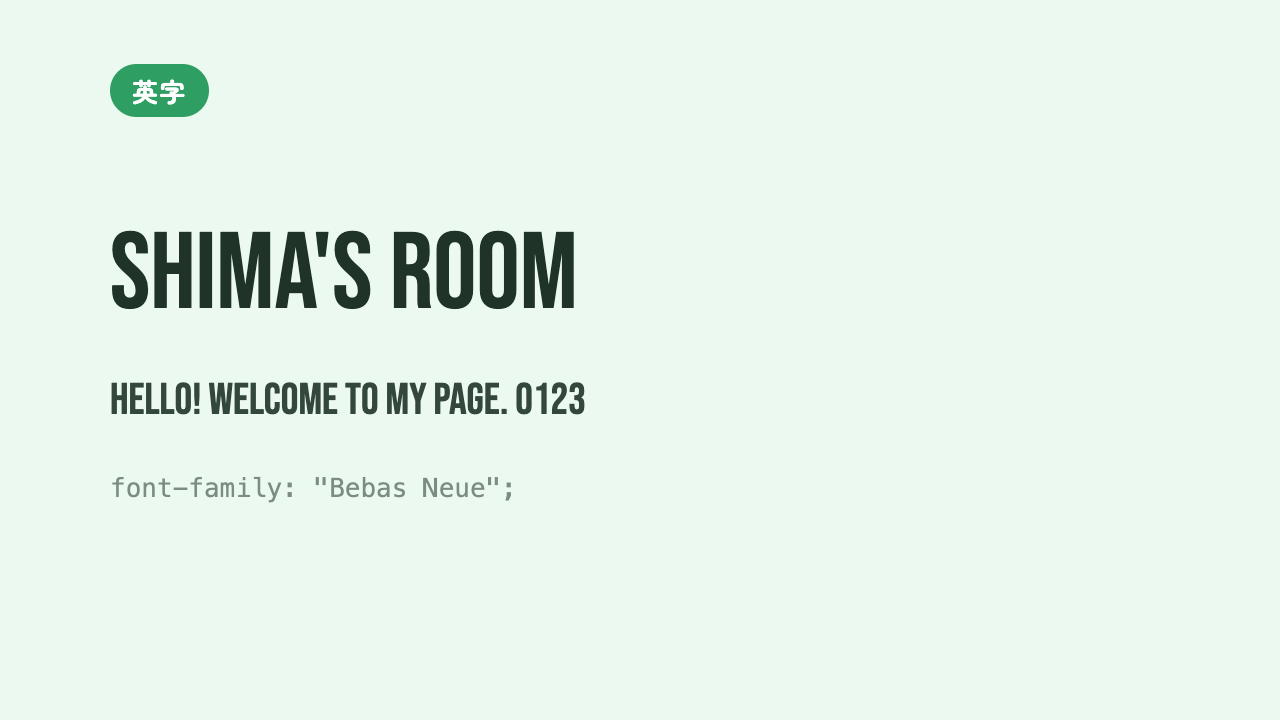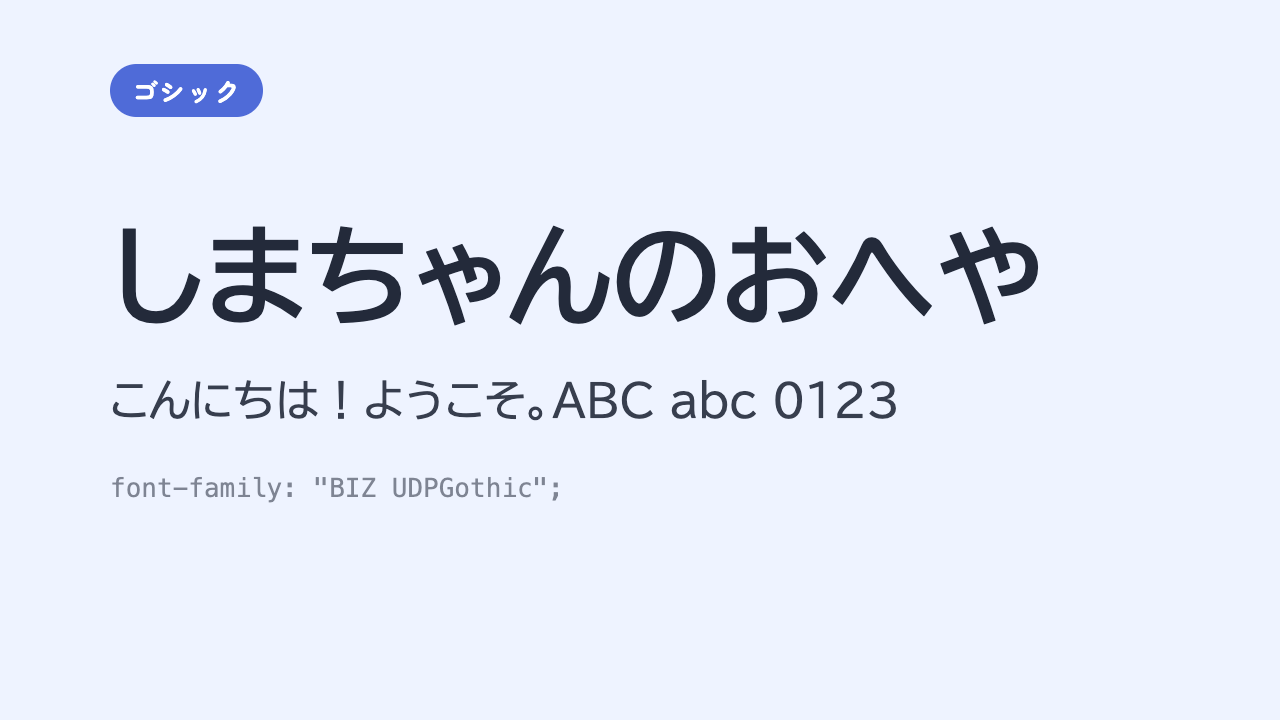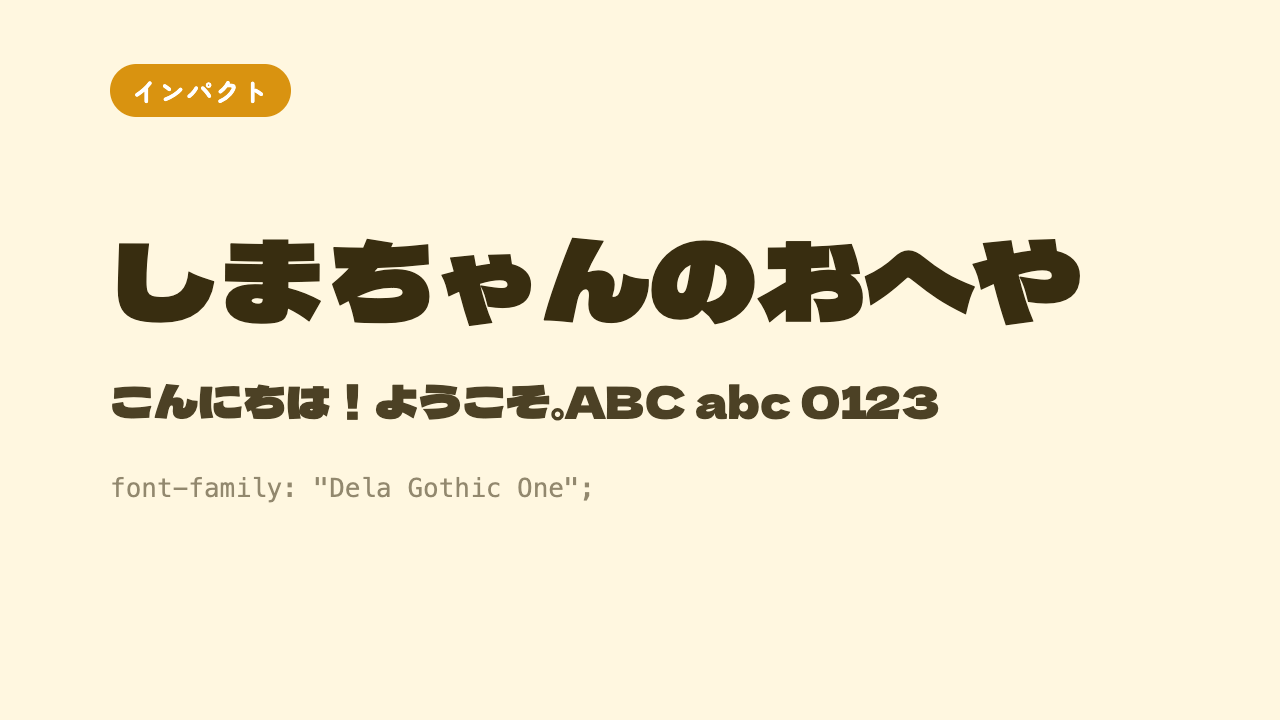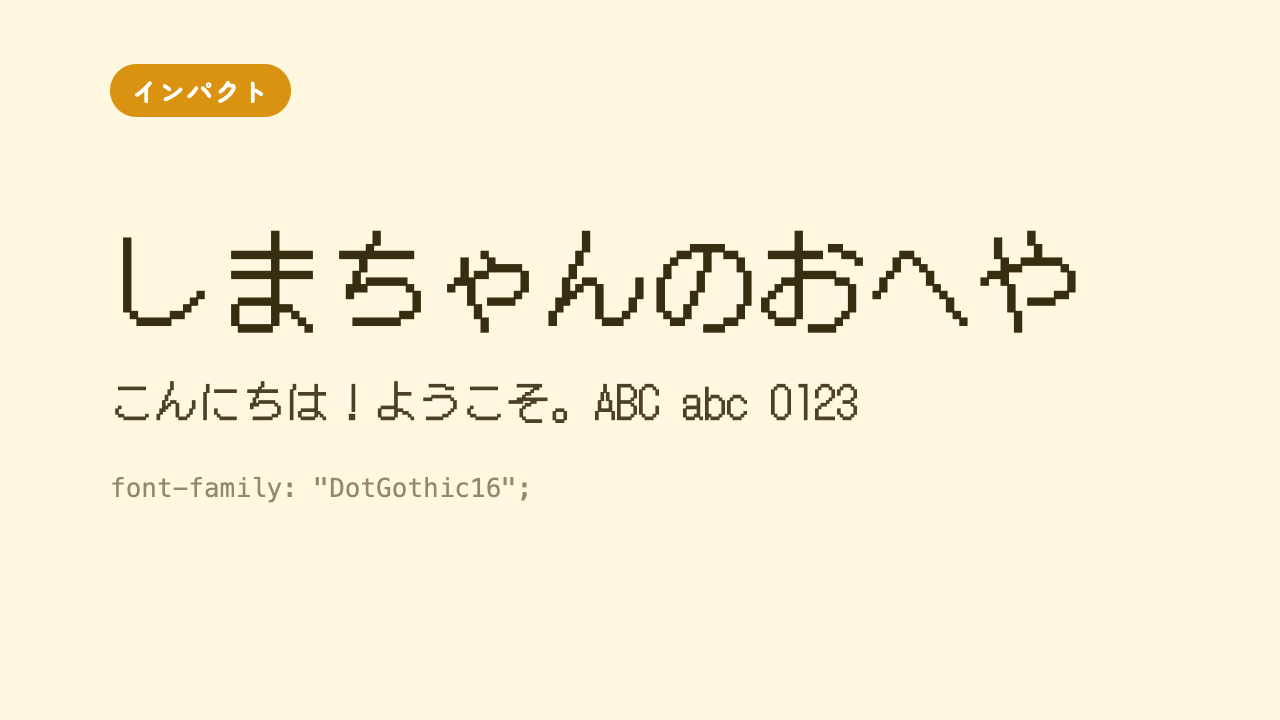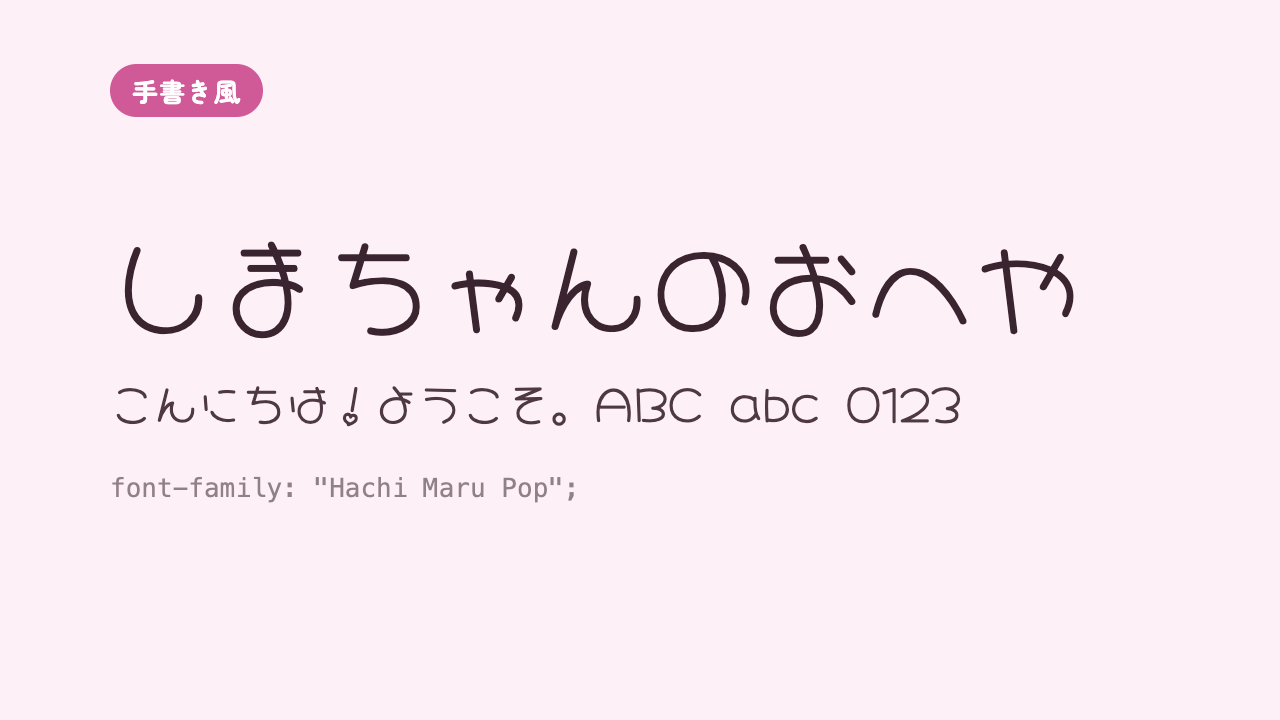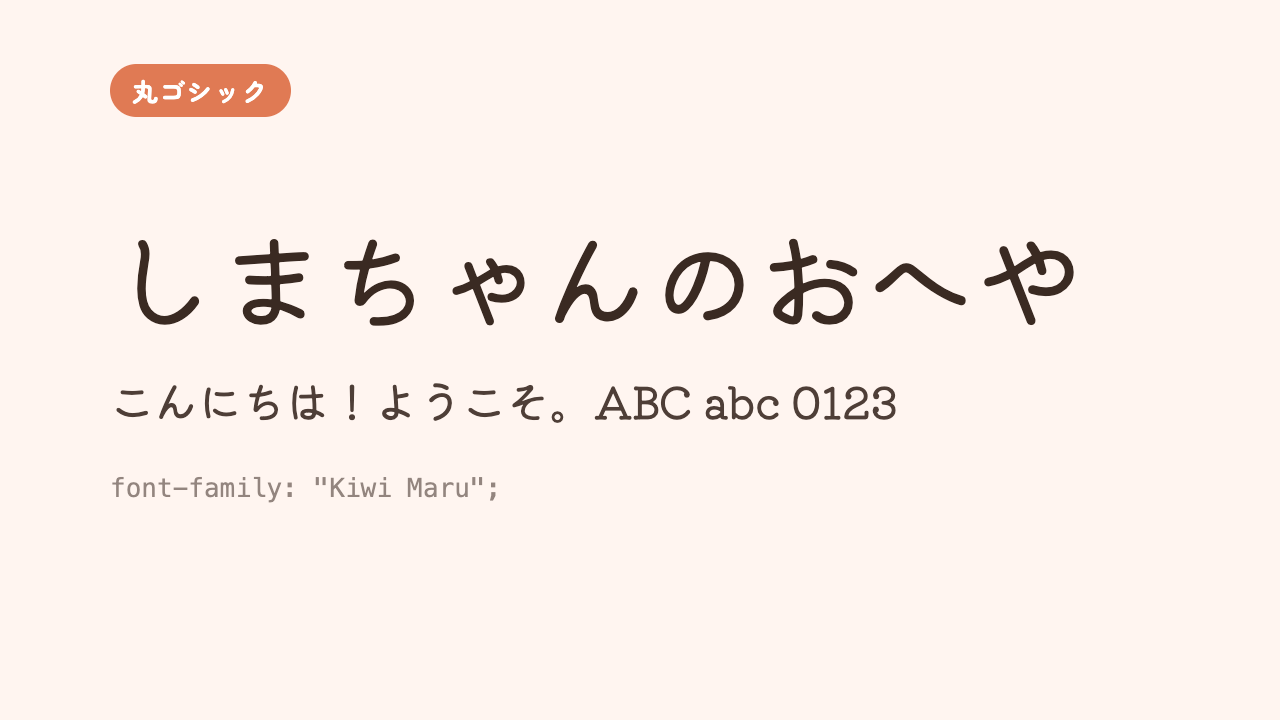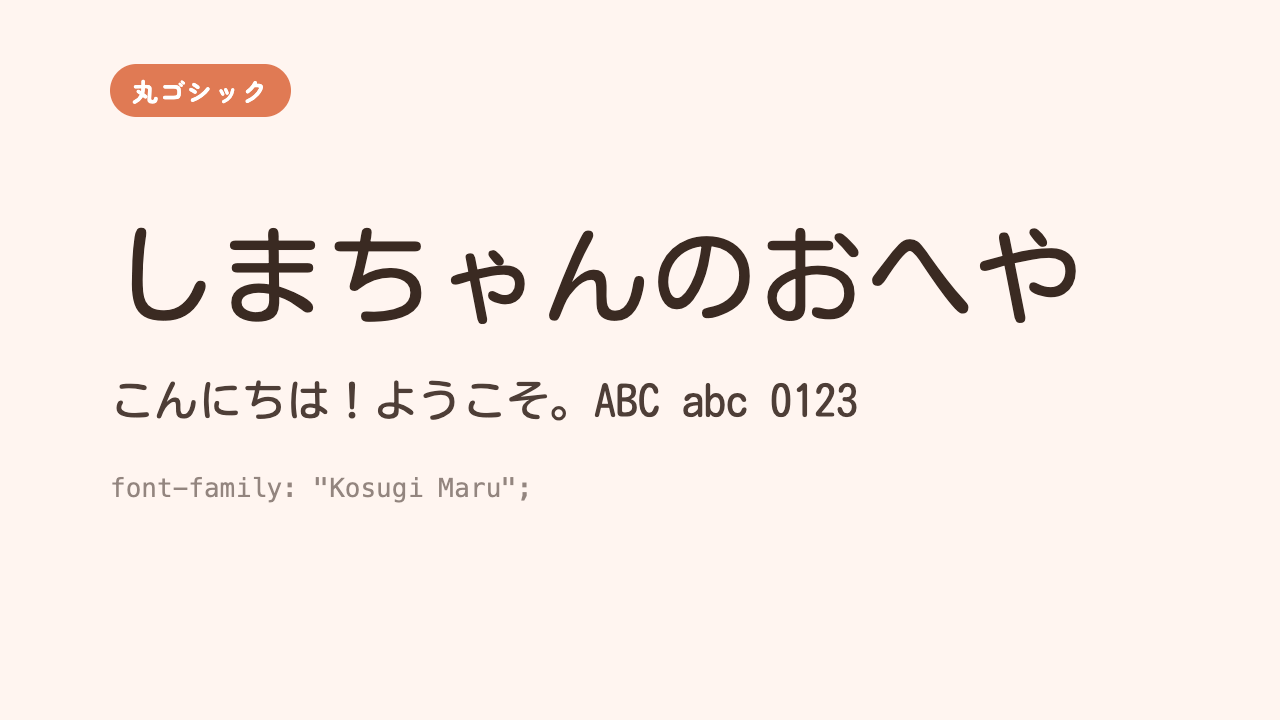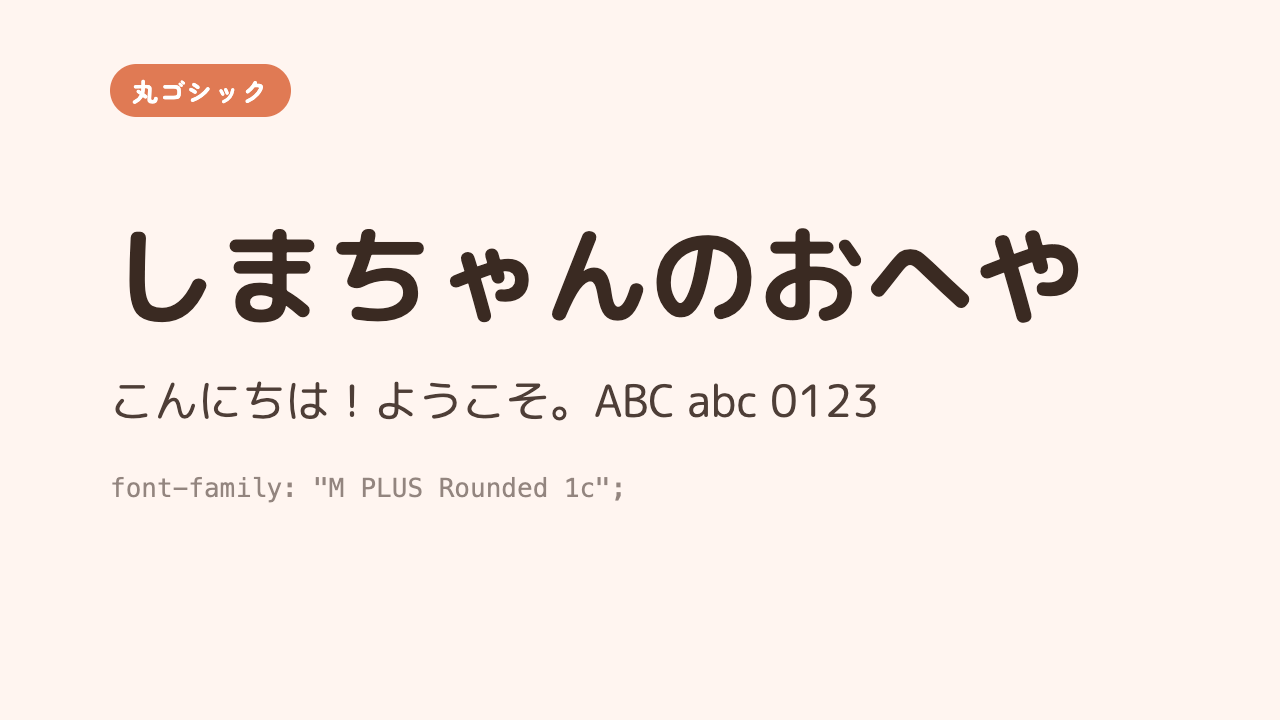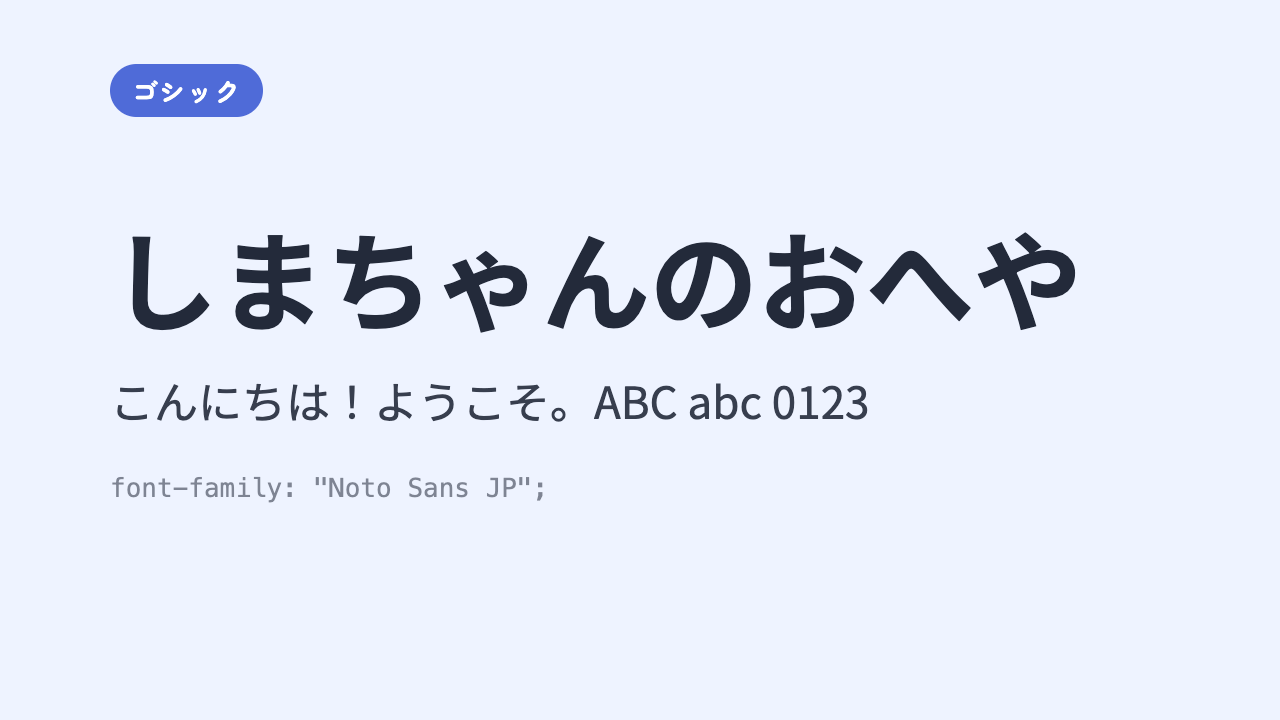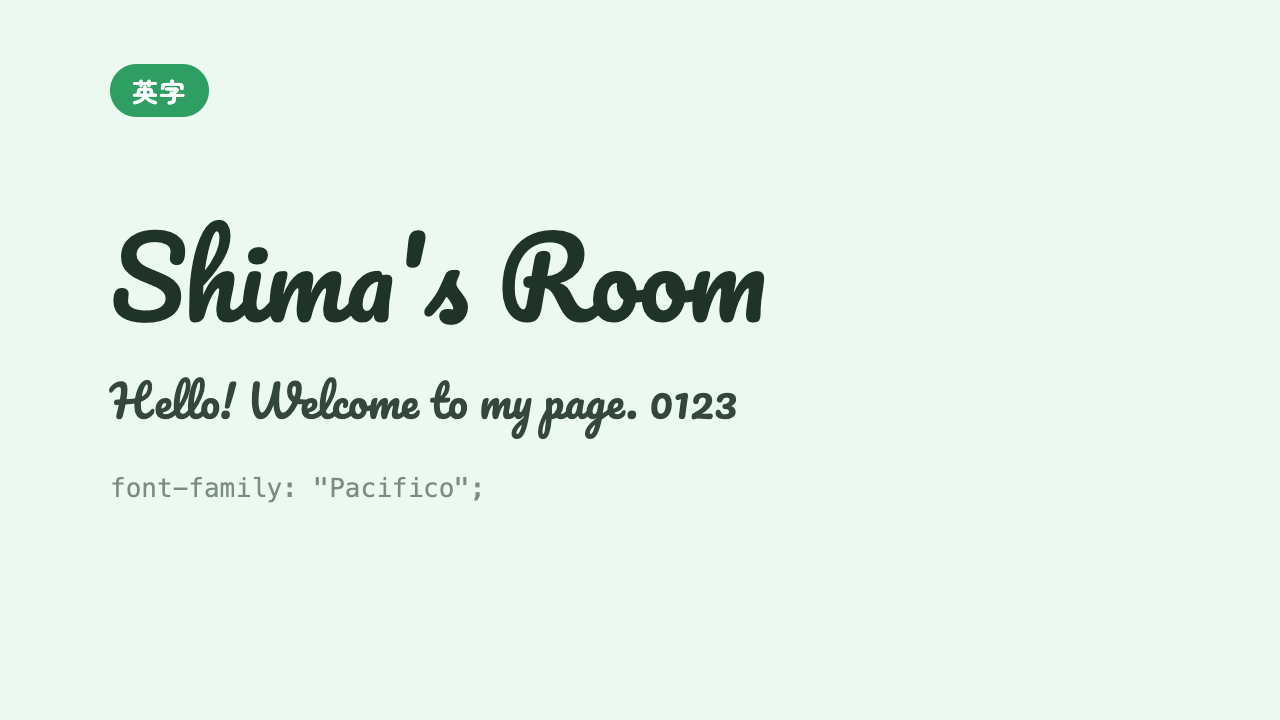
おすすめのGoogle Fonts
Google Fonts は数が多すぎて、どれを選べばいいか迷いがち。まるっこい・すっきり・しっとり・手書き風・インパクト大・英字のおしゃれ系——タイプ別に、実際に文字を出した見本つきで22種類をたっぷり紹介します。
Google Fonts は無料でたくさんのフォント(文字の形)が使えて便利ですが、種類が多すぎてどれを選べばいいか分からない——というのが最初のかべです。そこでこの記事では、初心者でも失敗しにくいおすすめをタイプ別に、実際に文字を出した見本つきでまとめました。全部使う必要はありません。眺めて「これ好き」と思うものを1つ2つ、ブックマークしておきましょう。
タイプ1:まるっこくて、やさしい(丸ゴシック)
角がまるい丸ゴシックは、やわらかくて親しみやすい印象。子ども向けのページや、あたたかい雰囲気を出したいときにぴったりです。日本語フォントの中でもいちばん人気のタイプ。
M PLUS Rounded 1c
丸ゴシックの大定番。太さも7段階から選べて使いやすい。
「しまちゃんのおへや」という文字が、角のまるいやわらかな丸ゴシック体で大きく表示されている見本
まるっこくて読みやすい、迷ったらこれ。本文にも見出しにも合う万能タイプです。
M PLUS Rounded 1c
Zen Maru Gothic
ふところが広く、ふっくら上品な丸ゴシック。
「しまちゃんのおへや」が、ふっくらまるみのある上品な丸ゴシック体で表示されている見本
M PLUS より少し落ち着いた大人っぽさ。やさしいけれど品もほしいときに。
Zen Maru Gothic
Kosugi Maru
軽やかで細めの丸ゴシック。すっきりかわいい。
「しまちゃんのおへや」が、細めで軽やかな丸ゴシック体で表示されている見本
線が細めなので、たくさん文字を並べても軽い印象。ポップだけどうるさくない。
Kosugi Maru
Kiwi Maru
まるでハンコのような、レトロでやわらかい丸ゴシック。
「しまちゃんのおへや」が、ハンコ風のレトロでやわらかい丸ゴシック体で表示されている見本
どこかなつかしい、ぽってりした形。個性を出したい見出しにおすすめ。
Kiwi Maru
タイプ2:すっきり読みやすい(ゴシック)
かざりの少ないゴシック体は、どんな場面でもハズさない安心のタイプ。長い文章でも読み疲れせず、まじめ・清潔な印象を与えます。「まず1つ入れるなら」の筆頭。
Noto Sans JP
Google が作った、世界標準の日本語ゴシック。困ったらこれで間違いなし。
「しまちゃんのおへや」が、クセのないすっきりした標準的なゴシック体で表示されている見本
クセがなく、どんなページにもなじみます。太さも9段階そろっていて、本文から見出しまで1つでまかなえます。
Noto Sans JP
Zen Kaku Gothic New
角ゴシックをていねいに整えた、現代的で美しいゴシック。
「しまちゃんのおへや」が、現代的でていねいに整えられた角ゴシック体で表示されている見本
Noto よりほんの少しおしゃれ。きれいめなサイトにしたいときの定番です。
Zen Kaku Gothic New
BIZ UDPGothic
「ユニバーサルデザイン」フォント。誰にでも読みやすいよう設計されている。
「しまちゃんのおへや」が、太めでくっきりした読みやすさ重視のゴシック体で表示されている見本
文字がくっきり大きめで、とにかく読みやすさ最優先。資料っぽいページや、大事なお知らせに向いています。
BIZ UDPGothic
タイプ3:しっとり上品(明朝)
たての線が太く、はらいのある明朝体は、大人っぽくて上品。落ち着いた雰囲気や、和風・高級感を出したいときに効きます。見出しに使うとぐっとしまります。
Shippori Mincho
「しっぽり」の名の通り、しっとり美しい明朝。和のページに。
「しまちゃんのおへや」が、しっとりとして美しい明朝体で表示されている見本
はらいやとめがきれい。和菓子屋さんのような、しっとりした世界観にぴったり。
Shippori Mincho
Zen Old Mincho
昔ながらの本の明朝を思わせる、正統派の明朝。
「しまちゃんのおへや」が、昔ながらの本のような正統派の明朝体で表示されている見本
物語や読み物のページに。ちゃんとした本を読んでいる気分になります。
Zen Old Mincho
Sawarabi Mincho
線が細めで、軽やかでモダンな明朝。
「しまちゃんのおへや」が、細めで軽やかなモダンな明朝体で表示されている見本
明朝の上品さはほしいけど重くしたくない、というときに。すっきりした余白が生きます。
Sawarabi Mincho
タイプ4:手書き風・かわいい
まるで人が書いたような手書き風のフォント。やわらかく、あたたかく、親しみのある雰囲気に。見出しやひとことメッセージに使うと、一気に「手作り感」が出ます。
Yomogi
やわらかいえんぴつ書きのような、ゆるくてかわいい手書き。
「しまちゃんのおへや」が、やわらかいえんぴつ書きのようなゆるい手書き風で表示されている見本
肩の力がぬけた、ゆるふわな雰囲気。日記や自己紹介にぴったりです。
Yomogi
Yusei Magic
マジックペンで書いたような、元気でポップな手書き。
「しまちゃんのおへや」が、マジックペンで書いたような元気でポップな手書き風で表示されている見本
太めで元気いっぱい。ポスターや、目立たせたいひとことに向いています。
Yusei Magic
Zen Kurenaido
ボールペンでさらっと書いたような、ナチュラルな手書き。
「しまちゃんのおへや」が、ボールペンでさらっと書いたようなナチュラルな手書き風で表示されている見本
自然でクセが少なめ。手書き風だけど本文にも使えるバランスのよさ。
Zen Kurenaido
Hachi Maru Pop
まんが風のぷっくりかわいい手書き。とにかく甘い雰囲気。
「しまちゃんのおへや」が、まんが風でぷっくりと甘くかわいい手書き風で表示されている見本
まるでシールやステッカーのような甘さ。かわいさ全開のページに。
Hachi Maru Pop
タイプ5:インパクト大(見出し・タイトル向け)
とても太かったり個性が強かったりする、見出し専用のタイプ。本文に使うと読みにくいので、タイトルやロゴ、目立たせたい1行だけに使うのがコツです。1か所キメると全体がしまります。
Dela Gothic One
これでもかと太い、超極太ゴシック。とにかく目立つ。
「しまちゃんのおへや」が、これ以上ないほど太い超極太ゴシック体で表示されている見本
タイトル1行にドンと使うと迫力満点。ポスターの見出しにおすすめ。
Dela Gothic One
RocknRoll One
太めで角がまるい、元気でポップな見出しフォント。
「しまちゃんのおへや」が、太めで角のまるい元気でポップな見出し向けフォントで表示されている見本
極太だけどまるくて親しみやすい。楽しい雰囲気の見出しにどうぞ。
RocknRoll One
Reggae One
グラフィティ風の、クセが強くてカッコいい見出しフォント。
「しまちゃんのおへや」が、グラフィティ風でクセが強くカッコいい見出し向けフォントで表示されている見本
ストリート感のあるおしゃれさ。個性でガツンといきたいときに。
Reggae One
DotGothic16
昔のゲームみたいな、ドット(点)で描いたレトロフォント。
「しまちゃんのおへや」が、昔のゲームのようなドット(点)で描かれたレトロなフォントで表示されている見本
レトロゲーム好きにはたまらないドット文字。ゲームやピクセルアートのページに最高です。
DotGothic16
タイプ6:英字のおしゃれフォント(ロゴ・見出しに)
日本語には効きませんが、英語のロゴやタイトルに使うとぐっとおしゃれになるのが英字専用フォント。サイト名やコーナー名など、英語のひとことに添えてみましょう。
Poppins
まんまるで幾何学的な、今どきの人気サンセリフ。
「Shima’s Room」という英字が、まんまるで幾何学的な今どきのサンセリフ体で表示されている見本
o がまんまるでかわいい。英語のサイト名やボタンをおしゃれに見せる定番です。
Poppins
Pacifico
なめらかな筆記体。サインみたいで、ぐっとこなれた印象に。
「Shima’s Room」が、なめらかな筆記体でサインのように表示されている見本
カフェの看板のような雰囲気。ロゴやキャッチコピーを1行だけおしゃれに。
Pacifico
Bebas Neue
背が高くてスタイリッシュな、全部大文字のフォント。
「Shima’s Room」が、背が高く全部大文字でスタイリッシュに表示されている見本
ずらっと並べるとポスターのようにカッコいい。数字やタイトルによく合います。
Bebas Neue
Playfair Display
上品でクラシックな明朝系(セリフ)。高級感を出したいときに。
「Shima’s Room」が、上品でクラシックなセリフ体で高級感をもって表示されている見本
ファッション誌のような大人っぽさ。英語の見出しに気品をそえます。
Playfair Display
選ぶときの3つのコツ
たくさん見てきましたが、実際に使うときはこれだけ意識すれば大丈夫です。
コツ中身
本文と見出しは分けてよい本文は読みやすいゴシック、見出しだけ好きなフォント——が失敗しにくい
使うのは1〜2種類まであれこれ混ぜると散らかる。読みこみも重くなる
雰囲気で選ぶやさしい=丸ゴシック、上品=明朝、元気=手書き、と気分で選べばOK
まよったら、本文は「Noto Sans JP」、見出しだけ好きなフォント——これだけで“ちゃんとした感”がぐっと出るよ。まずはお気に入りを1つ見つけてみてね〜
まとめ
1. Google Fonts はタイプ別に選ぶと迷わない——丸ゴシック / ゴシック / 明朝 / 手書き / インパクト / 英字
2. 本文は読みやすいゴシック、見出しだけ好きなフォント、が失敗しにくい黄金パターン
3. 使うのは1〜2種類まで。雰囲気で気軽に選んでOK